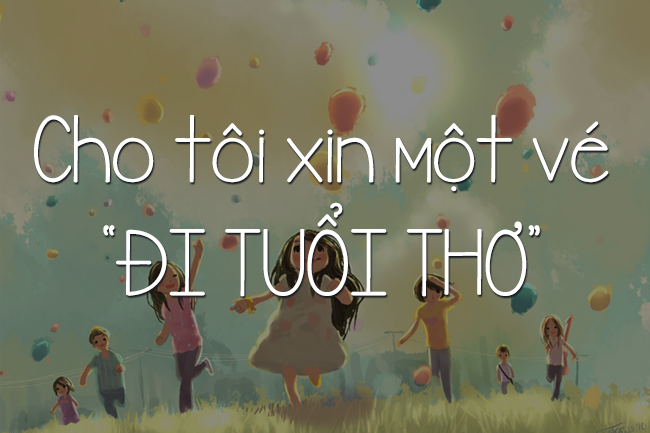
Banana Chip Muffins – một font chữ vui nhộn, đơn giản nhưng dễ thương, hoàn hảo cho nhãn mác, logo và các ứng dụng tương tự!
Nhà thiết kế: Brielle Lang